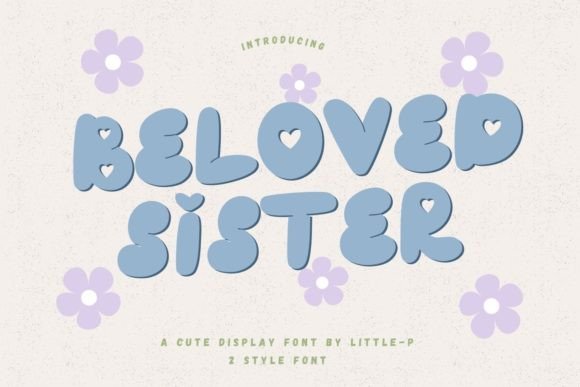
Beloved Sister
Beloved Sisterのような高品質の素材をお探しの場合、このプレミアムパッケージはクリエイティブなプロジェクトに素晴らしい選択です。
POD(オンデマンド印刷)製品、結婚式の招待状、またはソーシャルメディアのグラフィックを作成している場合でも、Beloved Sisterは理想的です。